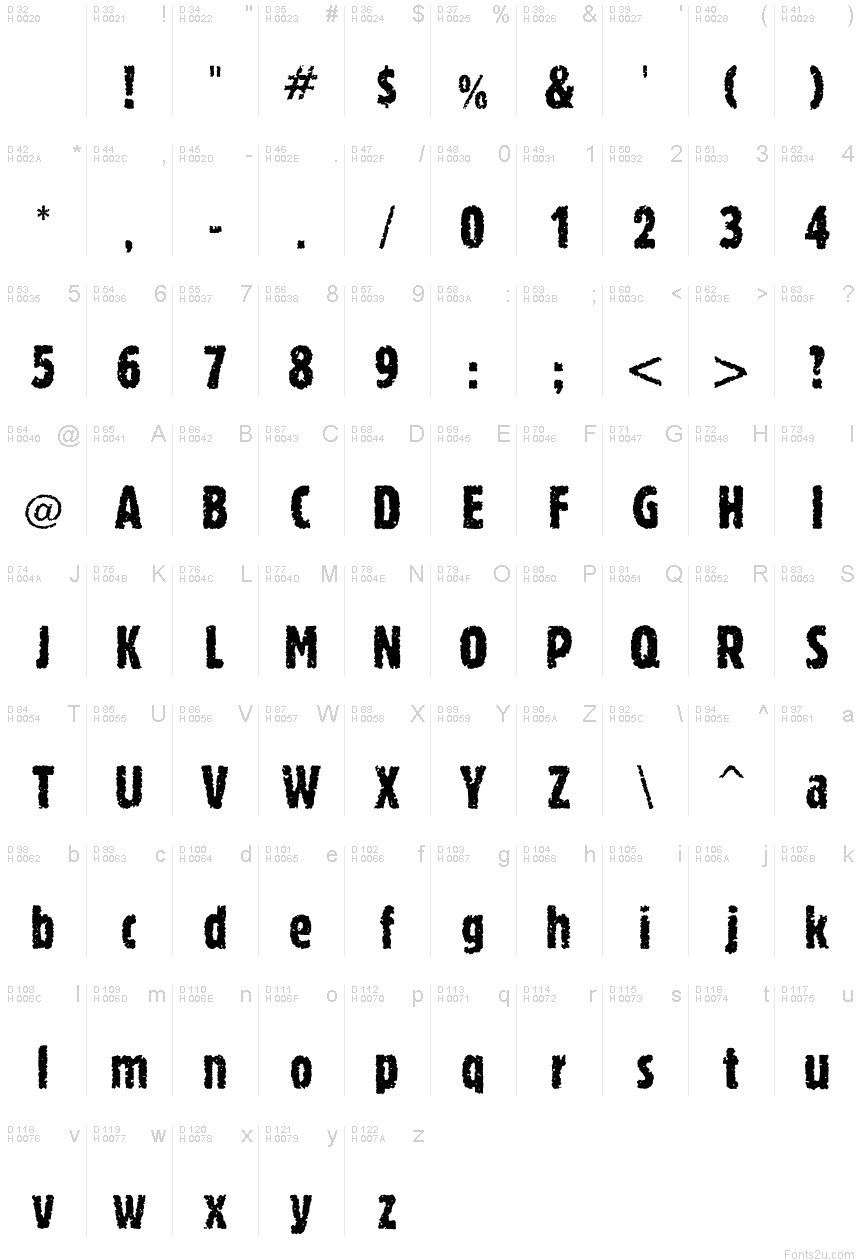
Romeo to darmowy krój displayowy o niechlujnej, "wygryzionej" przez tusz teksturze, dzięki której litery wyglądają na zniszczone i nieco buntownicze. Ciężkie formy pozostają proste w swojej konstrukcji, ale poszarpane krawędzie i ubytki nadają całemu krojowi surowy, grunge'owy charakter, daleki od wygładzonych efektów vintage.
To naturalny wybór na ulotki zespołów, tytuły horrorów, okładki zinów, plakaty imprezowe i odważne opakowania, gdzie szorstka powierzchnia jest częścią przekazu. Jako darmowy font, Romeo najlepiej sprawdza się w krótkich nagłówkach, tekstach na okładkach i logotypach, pozwalając swoim połamanym, nabrzmiałym literom zrobić największe wrażenie.
Romeo